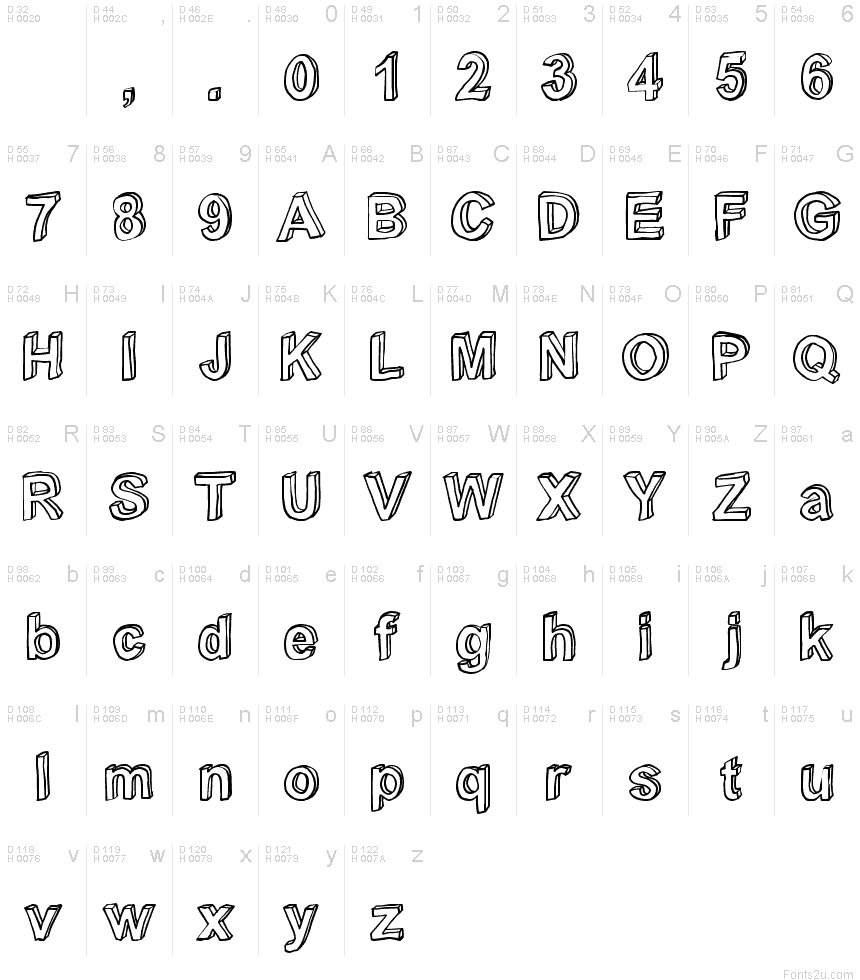
C rial 字体
C rial 字体家族,包含 2 款字体
C rial
由 J O E B O B graphics 设计的 C-rial 是一款免费的 3D 展示字体,采用开放式轮廓和锋利的侧边位移设计,使每个字形都带有折叠标识般的独特质感。不规则的轮廓柔化了几何结构,为立体字设计带来了一种俏皮且手绘的视觉风格。
这种倾斜的深度感创造出类似剪纸的效果,非常适合用于海报标题和音乐封面设计,而随性的轮廓则为活动传单和潮流品牌设计增添了一丝不羁的活力。如果您的包装设计或贴纸需要字体与插画完美融合,并传达出那种手绘草图般的构造感,不妨尝试这款免费字体。